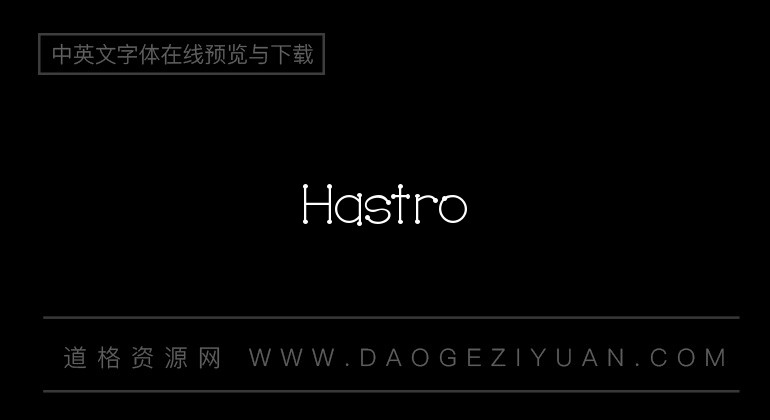
Hastro是一种现代化的无衬线字体,由设计师Daler Mukhiddinov于2020年创建。它的设计灵感来自于未来主义和科技感,其设计特点包括大胆的线条和圆润的笔画。 Hastro字体包括多种字重和斜体,适用于各种设计应用,如广告、标志、海报、包装和数字设计等。它的设计简洁、明快,字母间距离较窄,具有高度的可读性和视觉吸引力。 总之,如果您正在寻找一种现代化且独特的无衬线字体,Hastro可能是一个不错的选择。内容介绍
Hastro是一款非常不错的手写艺术字体,具有很好的视觉感,适合于文化类的宣传设计、商业类品牌的广告和产品包装设计以及个性化文字排版等较多场景。